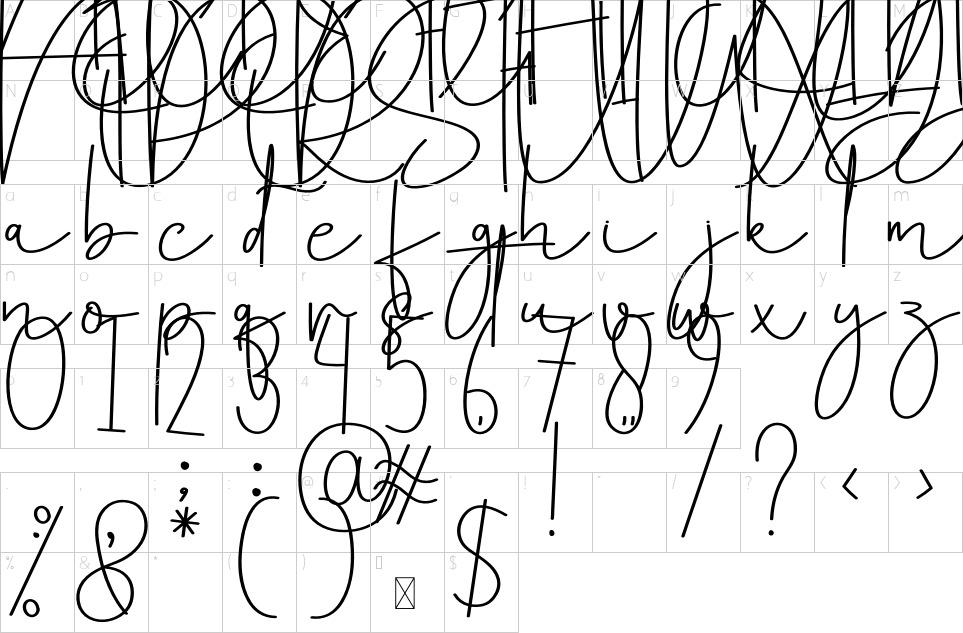
Descubra Delightful Font, uma fonte elegante e versátil disponível para Windows e Mac. Desenvolvida por scratchones, Delightful é uma escolha perfeita para designers que buscam adicionar um toque agradável ao seus projetos digitais. Com 133 downloads até agora, não hesite em experimentar sua delicadeza e facilidade de uso. Seja para criar anúncios de moda, design gráfico ou simplesmente estabelecer uma atmosfera amigável no seu website, Delightful é uma excelente opção. Descubra o que há de tão especial sobre essa fonte gratuita hoje.